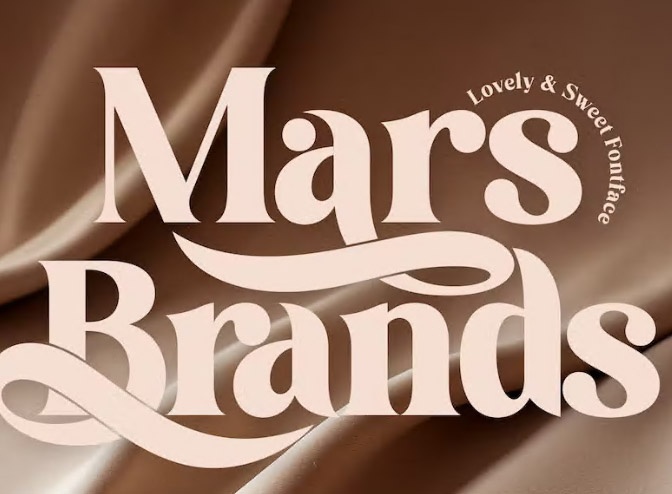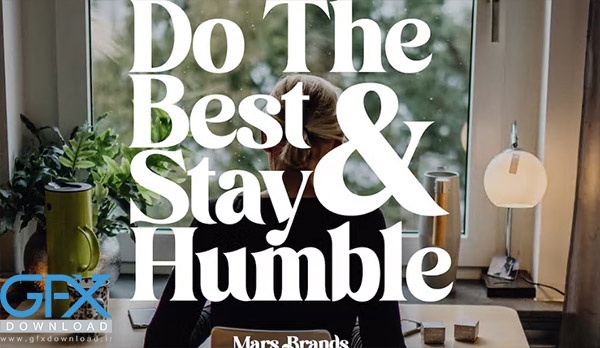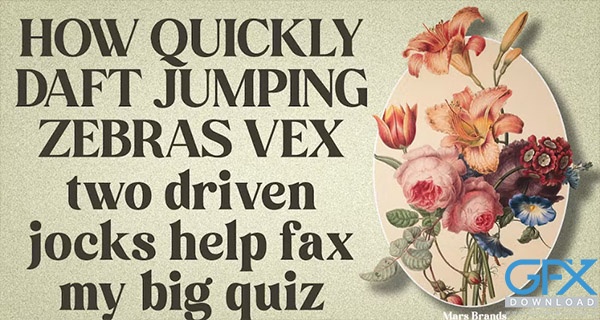
دانلود فونت انگلیسی Mars Brands
فونت انگلیسی Mars Brands
دانلود فونت انگلیسی زیبا Mars Brands
یک فونت سریف کاملاً زیبا با طراحی دوست داشتنی است. این تایپ فیس شامل جایگزین های سبکی زیبا و لیگاتورهای اختیاری است. دانلود فونت انگلیسی Mars Brands این فونت طیف وسیعی از ایده‌های کاردستی، از کارت‌ها، نام تجاری محصول، برچسب‌ها و موارد دیگر را ارتقا می‌دهد. این فونت دارای کد PUA است، که به این معنی است که می‌توانید به راحتی به همه حروف‌ها و حروف‌ها دسترسی داشته باشید. شامل مارک های Mars (otf، ttf، woff، woff2).